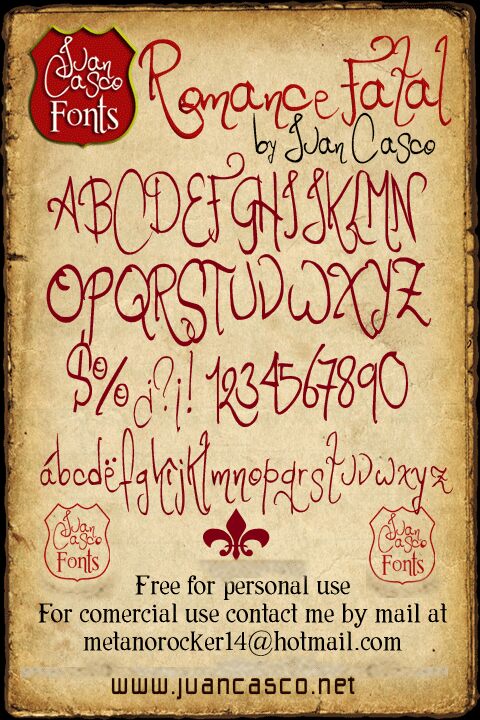
Romance Fatal 2.00 di Juan Casco è un font corsivo manoscritto e drammatico, gratuito, caratterizzato da un ampio movimento calligrafico. Le sue lettere con anelli stretti alternano tratti sottili e curve più piene. Discendenti lunghe e ampi fregi conferiscono alla scrittura una silhouette inequivocabilmente romantica.
Può creare un titolo teatrale per la narrativa sentimentale o per la cartoleria di nozze. Si adatta inoltre al packaging di profumi di nicchia. In questi contesti, le anse oversize possono fungere da linee decorative, collegando il lettering a illustrazioni floreali o simili a nastri.